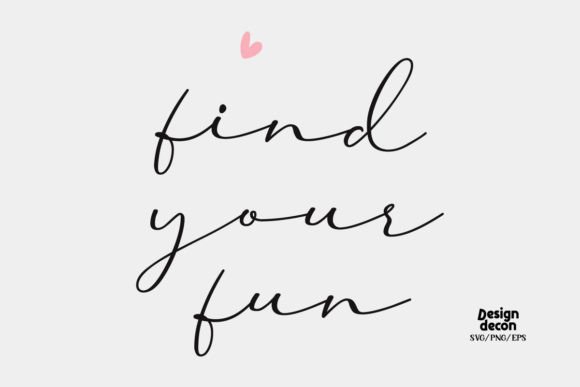
Photography Overlay Handwriting SVG
Пошук відповідних елементів дизайну може бути складним, але Photography Overlay Handwriting SVG пропонує виняткову колекцію, яка миттєво покращить вашу роботу.
Створений з високою точністю, Photography Overlay Handwriting SVG забезпечує чисті вектори, плавну типографіку та комерційну ліцензію для вашого спокою.
Незалежно від того, чи створюєте ви продукти POD (друк на вимогу), весільні запрошення або графіку для соціальних мереж, Photography Overlay Handwriting SVG стане ідеальним вибором.